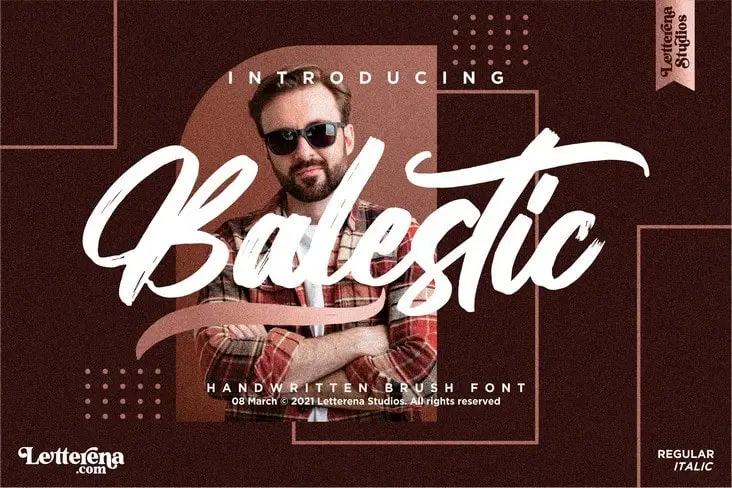
A Balestic Brush Font é uma elegante fonte escrita a mão que apresenta traços grossos e finos perfeitos para projetos requintados do mundo digital à realidade. Suave ao toque, esta fonte criada pela 99designs se destaca por sua personalidade única, tornando-a ideal para uma ampla gama de projetos. Seja para criar um logo chamativo e distintivo ou produzir tags de embalagens sofisticadas, este traço suave mas robusto está sempre pronto para dar aquele toque especial aos seus projetos. É perfeito para personalizar desde etiquetas e logotipos até designs de livros e cartões de visita. Para qualquer projeto que busque um ar elegante e um toque de elegância, a Balestic Brush Font é sua escolha ideal.